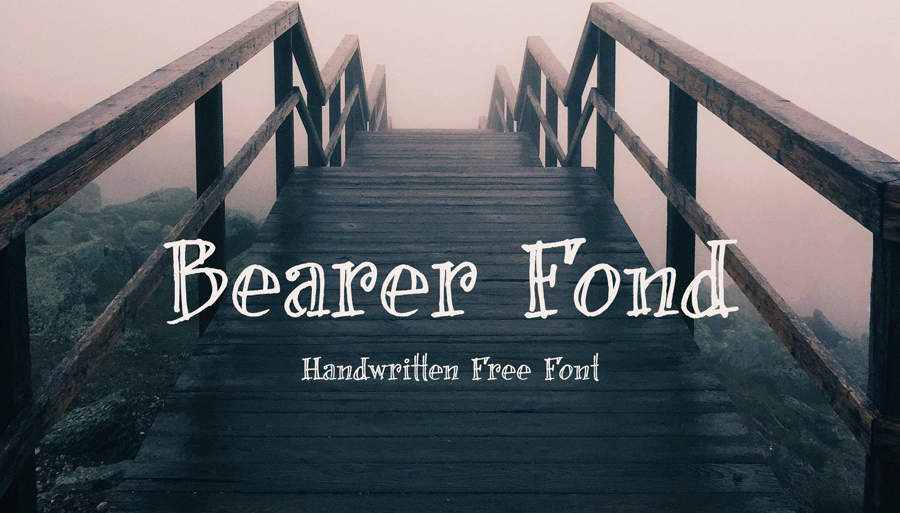
A fonte “Bearer Fond” oferece uma experiência única de escrita manuscrita natural que é perfeita para quem procura uma aparição de estilo único e autêntico no seu projeto. Como designer Hamilton criou, essa fonte representa a beleza inigualável das escritas livres e naturais, tornando-a ideal tanto para aplicativos digitais quanto para impressões profissionais. Se você busca personalizar um design com uma aparência livre e natural sem parecer repetitivo, “Bearer Fond” pode ser o fonte perfeito para transformar seus projetos em algo único e autêntico. Este é o ideal para os criadores que buscam inovação e originalidade no seu trabalho gráfico.